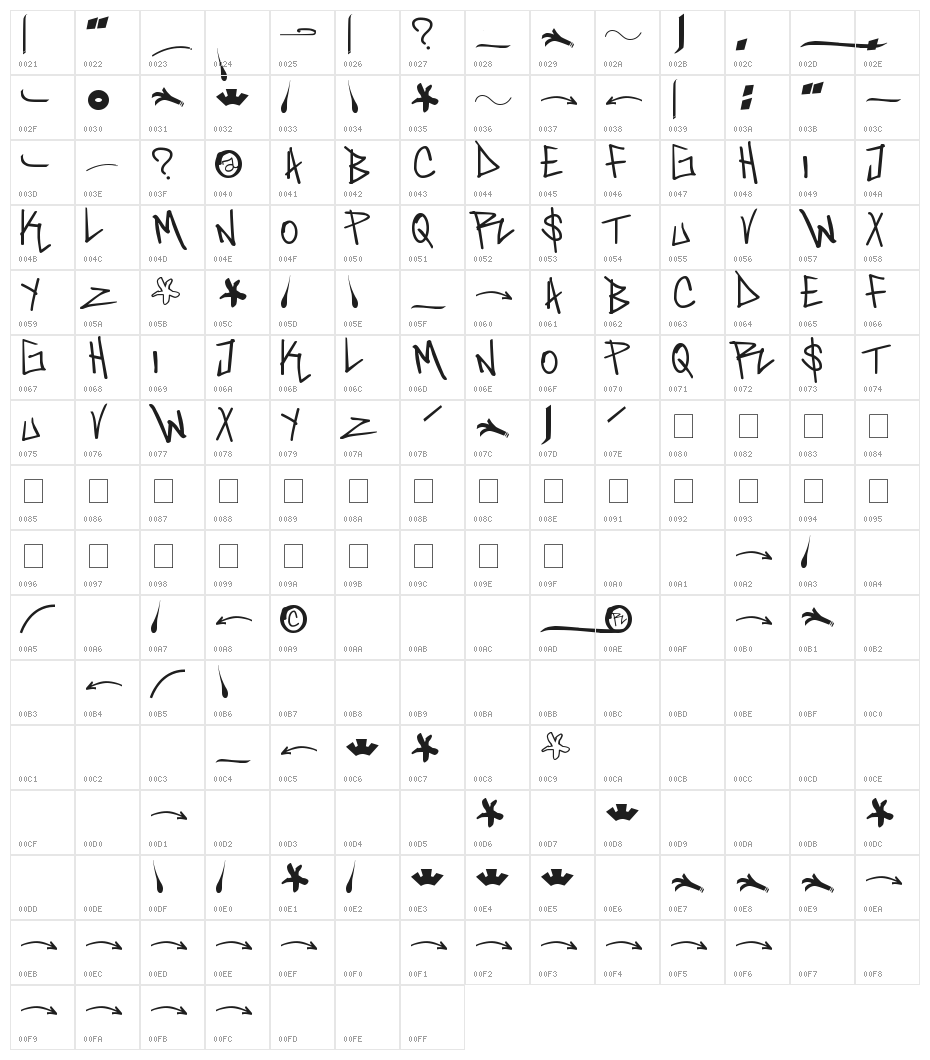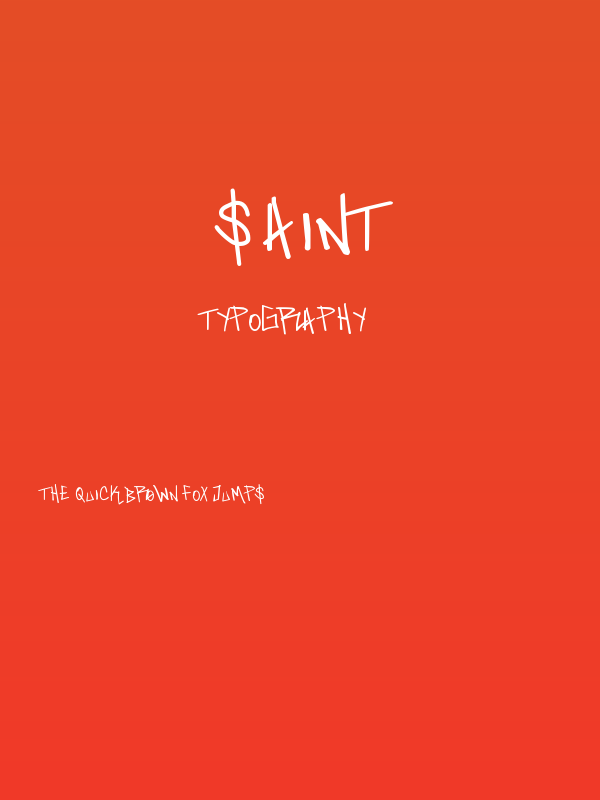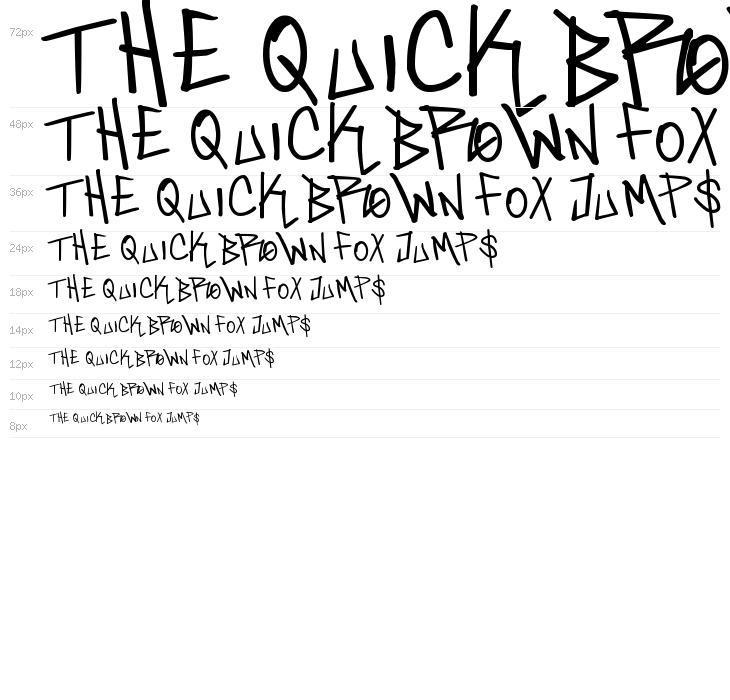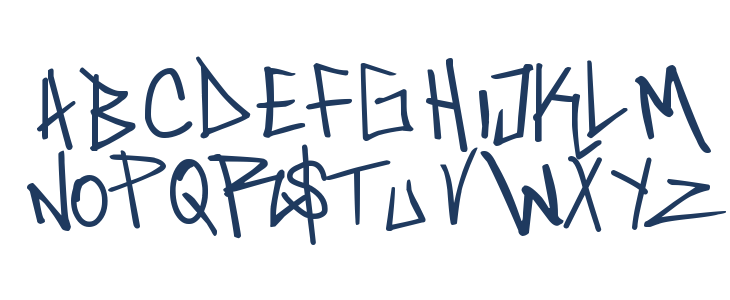
saint Font
✎ Graffiti
| Kategorien | Graffiti |
| Gesamtstil | Modern, Edgy |
| Anwendungsfall | Logos, Posters, Creative Projects |
| Vorgeschlagene Projekte | Ideal for graffiti art, streetwear branding, music album covers, and creative posters. |